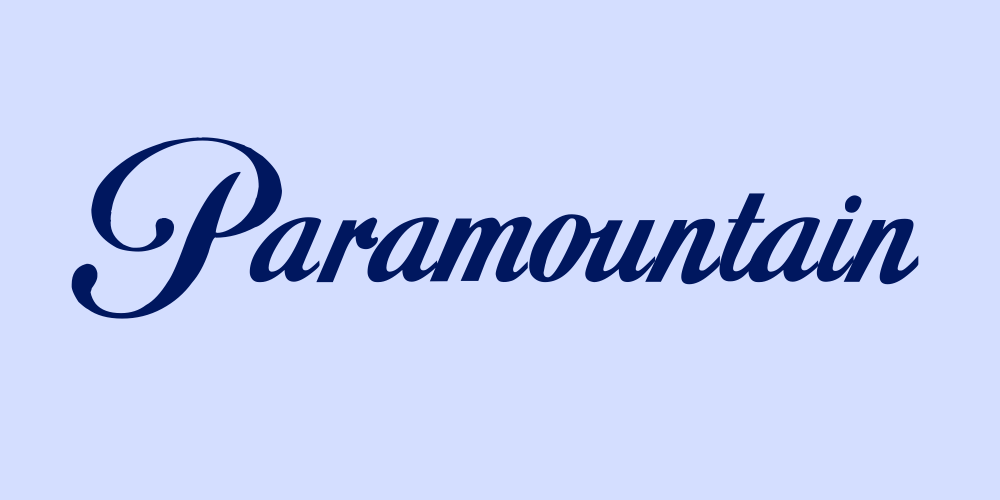
A fonte Paramountain foi desenvolvida especialmente para atender a solicitação do designer Jack Lyric West (629Lyric), buscando aprimorar as funções do famoso grupo de fonts Paramount. Esta nova font é uma evolução da família de fonts Paramount, apresentando novas características que permitem um design ainda mais fino e versátil. Com seu estilo elegante e moderno, a Paramountain será o complemento perfeito para qualquer projeto visual. Seja você um designer gráfico ou editor de conteúdo, certamente encontrará na Paramountain font aquilo com que está procurando – uma fonte que vai além dos limites da simplicidade. Não hesite em experimentar esta paixão criativa e revolucionária em seu próximo projeto.